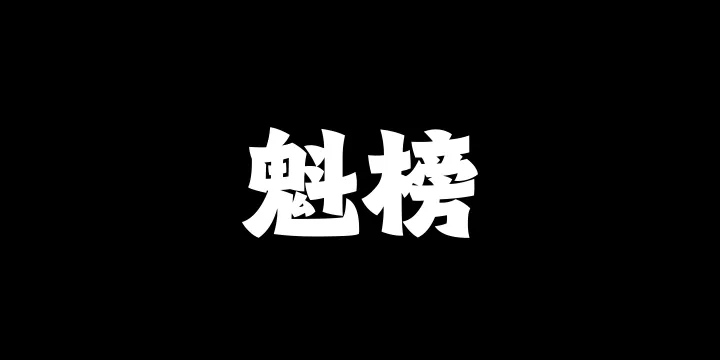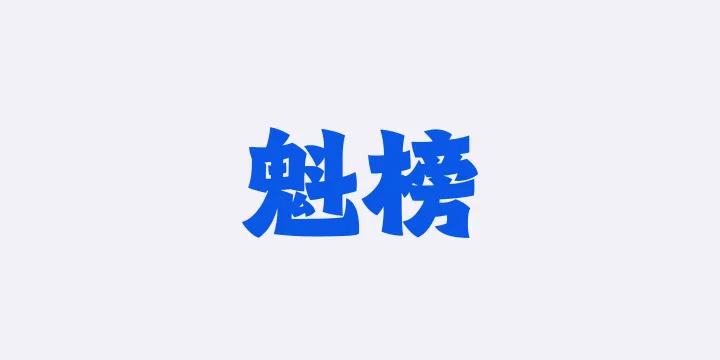
山海魁榜W By 山海字库 商用字体
字体全名: 山海魁榜W
字体简介: 山海魁榜,包含简繁汉字9169个,是一款标题字体。该字体以楷体为骨架,同时将魏碑之魂注入字体造型之中。结体紧密,行笔有力,错落有致,险中求稳。多用方笔,险劲而富于变化,行笔轻重交错,刚劲果断。这款字体气势磅礴,彰显楷书和魏碑的气韵,同时兼顾排版的实用性,适合应用于传统节庆场合、书籍封面、影视娱乐等多样的使用场景。